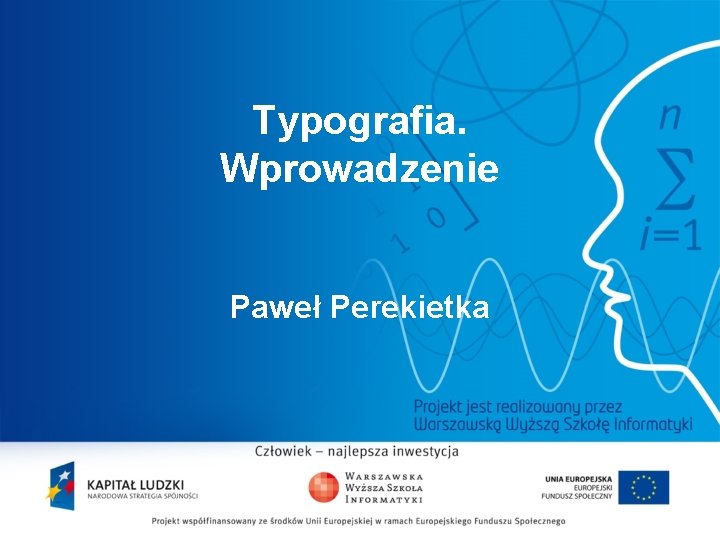
Typografia. Wprowadzenie Paweł Perekietka 2
Co to jest typografia? „Typografia – dziedzina sztuki zajmująca się graficznym ukształtowaniem tekstu i obrazów w publikacjach”. (J. Jarzina, Tajniki typografii dla każdego, Warszawa 2003) „Wypowiedź bez zróżnicowanej intonacji (…) jest nużąca i przez to bardzo słabo przyswajalna. W języku pisanym rolę intonacji przejmuje na siebie forma graficzna tekstu”. (A. Blikle, Komputerowa edycja dokumentów dla inteligentnych) 3
Czytelność a wyrazistość czcionek Garamond Times New Roman Georgia Arial Tahoma Courier Comic Sans MS 4
„Systematyka” pisma drukowanego Krój pisma oznacza najpierw cechy wizualne pisma (np. grubość, szerokość). Czcionka jest słowem oznaczającym pierwotnie ołowiany element ze znajdującym się na nim konkretnym znakiem pisma (np. literą). Font to zapisana cyfrowo informacja o kształcie znaku pisma. Terminy te traktuje się dzisiaj jak synonimy. 5
Elementy dokumentu tekstowego a skład Trzy podstawowe elementy dokumentu: tytuł śródtytuły część właściwa (treść) Tekst właściwy (treść) powinien być składany czcionką szeryfową (antykwa renesansowa). Tytuły i śródtytuły należy składać czcionką bezszeryfową (antykwa linearna bezszeryfowa). 6
Metody wyróżniania fragmentów tekstu Niepoprawne metody wyróżniania tekstu to: podkreślenie pisanie WIELKIKI LITERAMI pisanie wyrazów z e s p a c j ą pomiędzy każdymi dwoma literami Poprawnymi metodami wyróżniania tekstu są: wytłuszczenie (stosowanie czcionki półgrubej) pochylenie rozstrzelenie (spacjowanie) 7
Akapity Co to jest akapit? 1. «ustęp tekstu zaczynający się od nowego wiersza» 2. «początkowy wiersz nowego ustępu» (źródło: http: //sjp. pwn. pl/slownik/2549156/akapit) 8
Błędy formatowania akapitu Typowe błędy formatowania akapitu: styl „mieszany” wyróżniania akapitu (wcięcie akapitowe i odstęp akapitowy) zbędne wcięcie akapitowe źle dobrany odstęp między wierszami źle dobrane odstępy przed akapitem tytułowym i po nim problemy ostatniego wiersza akapitu: sieroty i wdowy akapit justowany bez dzielenia wyrazów 9
Elementy strony Obszary (elementy) strony to: margines górny i nagłówek (główka) strony, margines dolny i stopka, margines lewy i prawy, obszar tekstu (tabel, grafik itp. ) i przypisów. 10